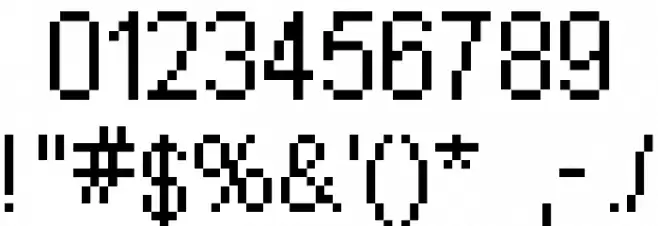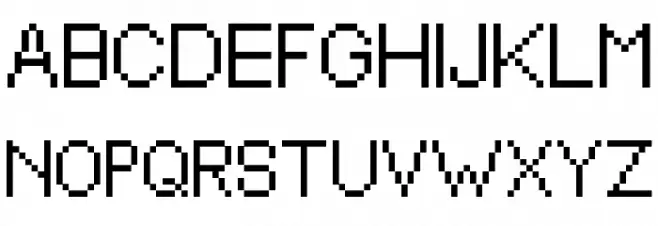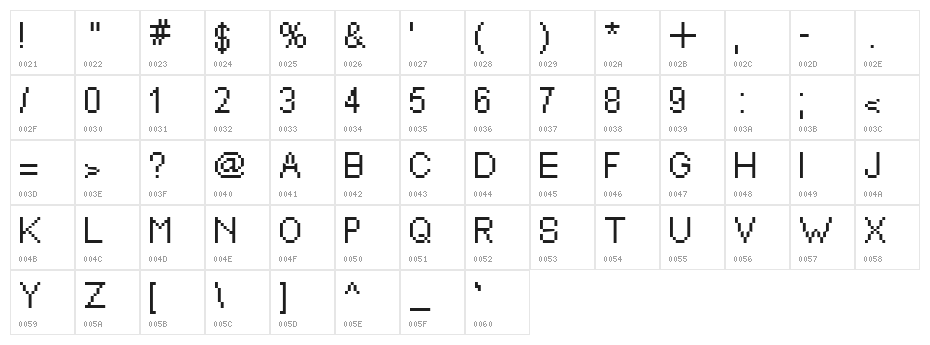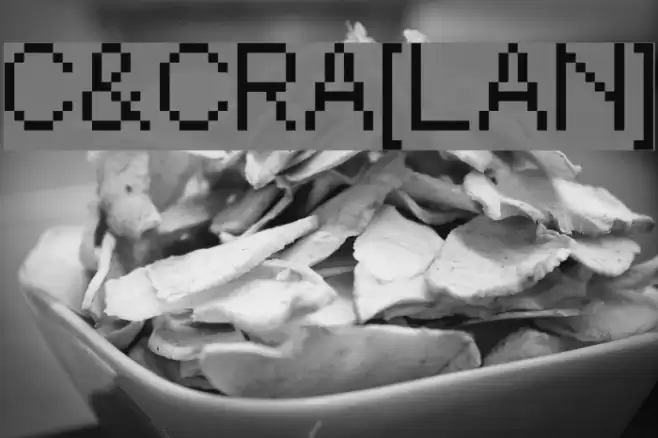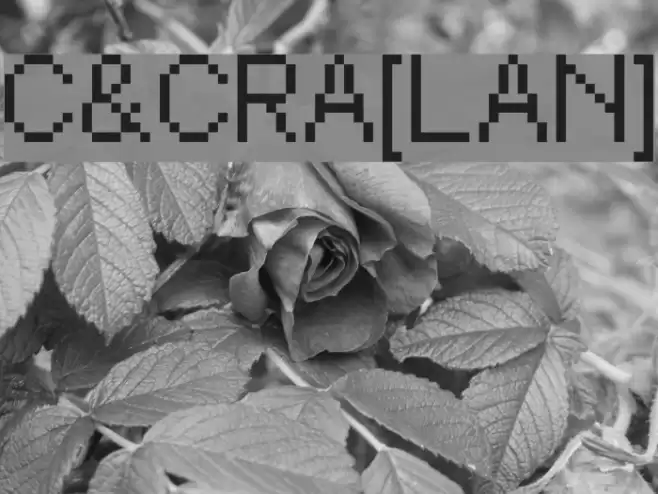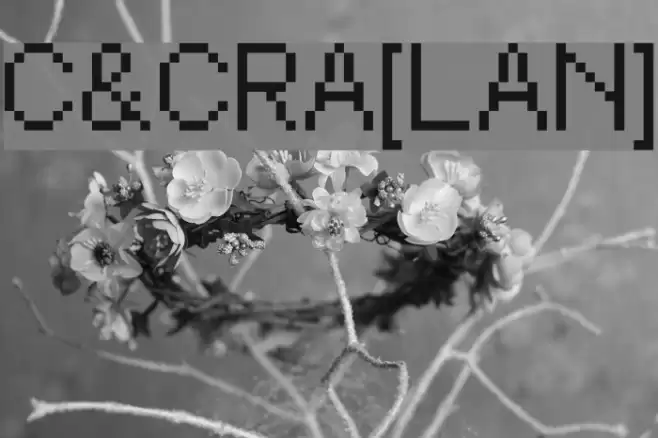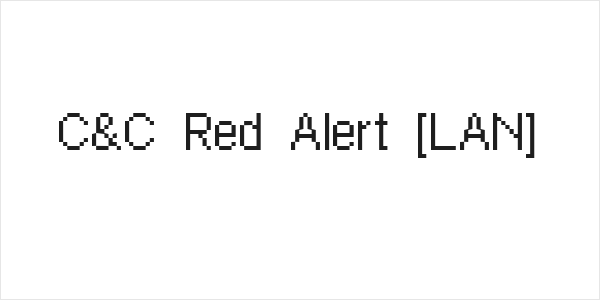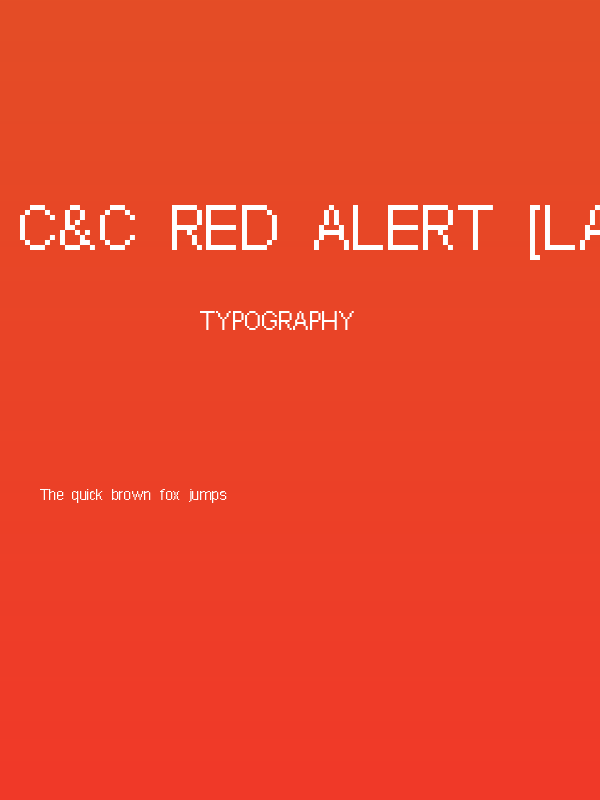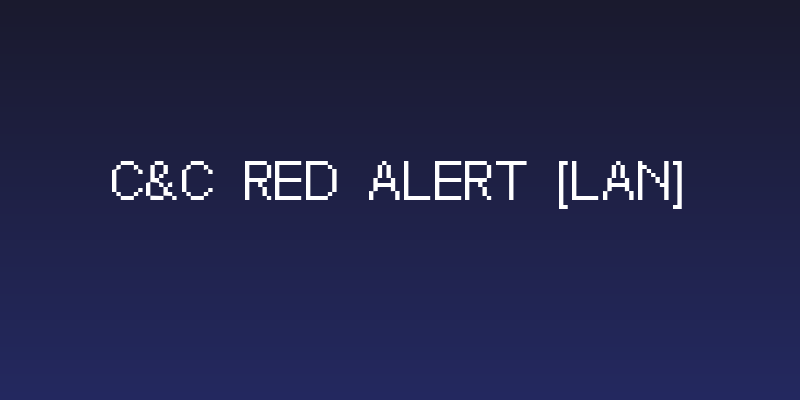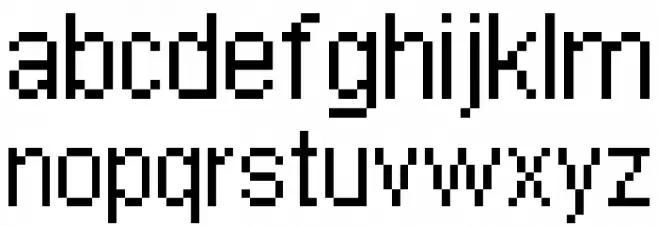
C&C Red Alert [LAN] Font
| カテゴリ | Pixel |
| 全体的なスタイル | Retro, Digital |
| 用途 | Logos, Headlines, Digital Art |
| おすすめプロジェクト | Ideal for retro video game designs, digital art projects, and any creative work that seeks to capture the essence of early computing aesthetics. |